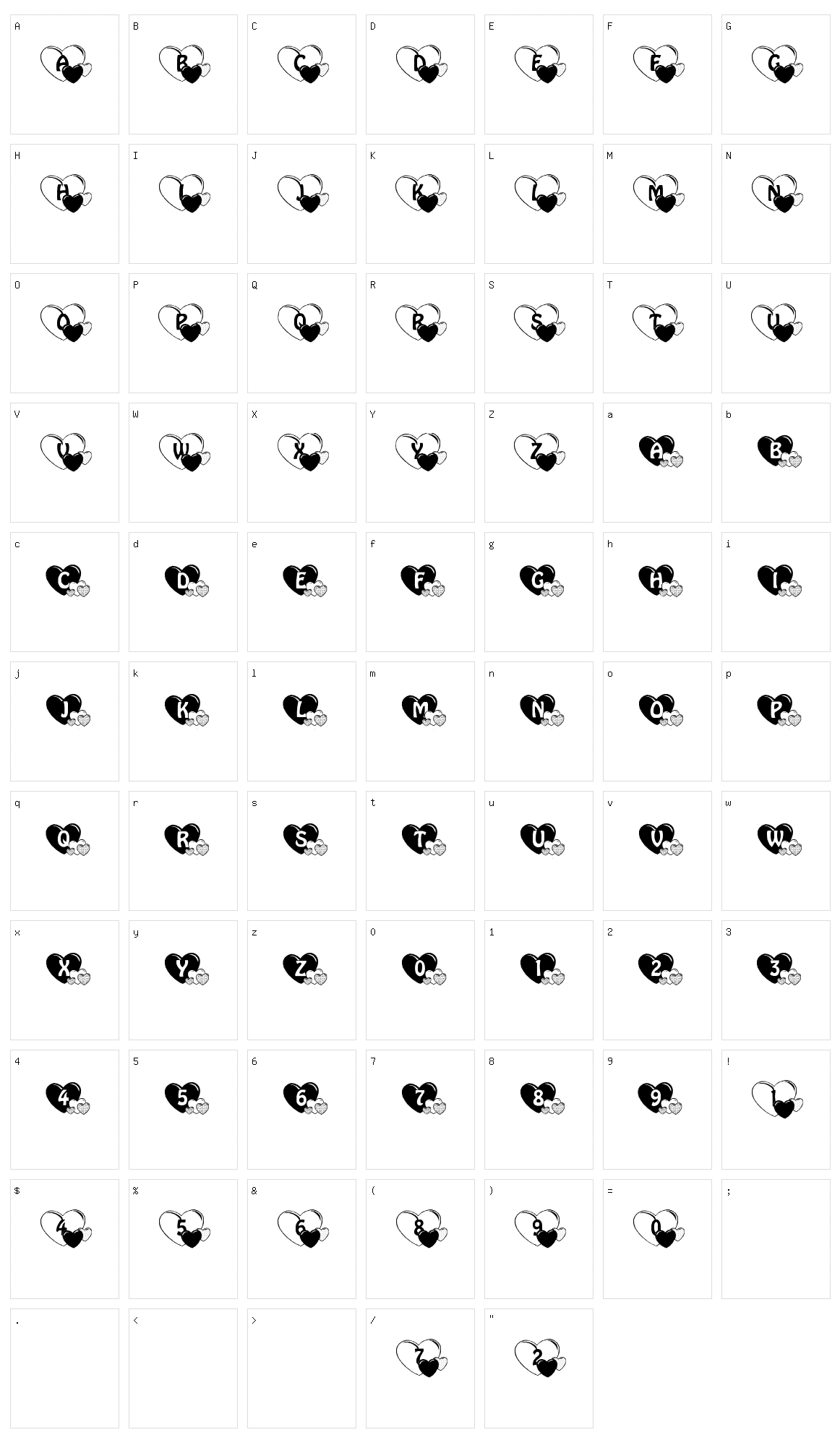
Diese Schrift habe ich für meine Mami zum Muttertag gemacht. Wir nehmen diesen Tag nicht
sehr ernst und machen uns eigentlich ein wenig lustig darüber. Denn schon seit ich denken
kann, ist meine Mutter von dem Tag nicht sehr begeistert. Sie vertritt die Meinung, wenn
in einer Familie nur am Muttertag die Aufgaben einer Mutter wertgeschätzt werden, und ihr
nur da im Haushalt geholfen werden sollte, dann solle man ihn besser gar nicht feiern. Es
ist bei uns schon ein Ritual, dass ich Mami morgens mit den Worten Lieb Mütterlein begrüße
und damit ein Gelächter meiner Mutter ernte. Schließlich weiß sie auch ohne Muttertag, dass
ich sie lieb habe.